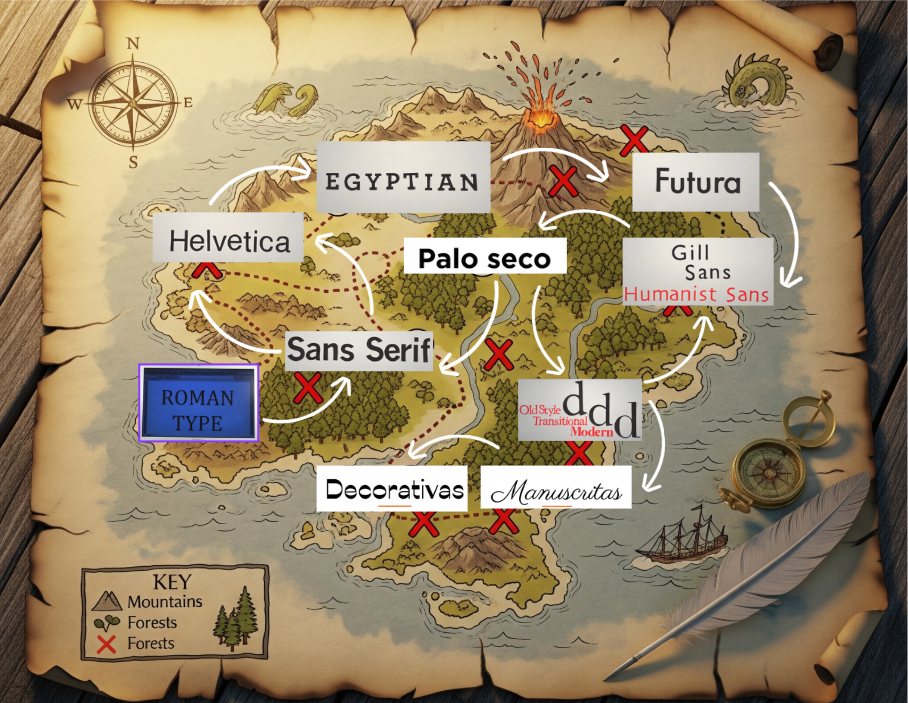
JUEGO TIPOGRAFIAS
1 Tiene raíces clásicas, con remates elegantes. 2 Se caracteriza por no tener remates en las letras. 3 Es una tipografía muy popular, creada en Suiza. 4 Tiene serifas gruesas y rectas,con aspecto sólido. 5 Tipografía geométrica. 6 Sin serifas pero con formas orgánicas y cálidas. 7 Otro nombre para las tipografías sin remates. 8 Tres etapas históricas de las serifas. 9 Sus letras parecen escritas a mano, fluidas. 10 Son tipografías con formas llamativas, usadas.